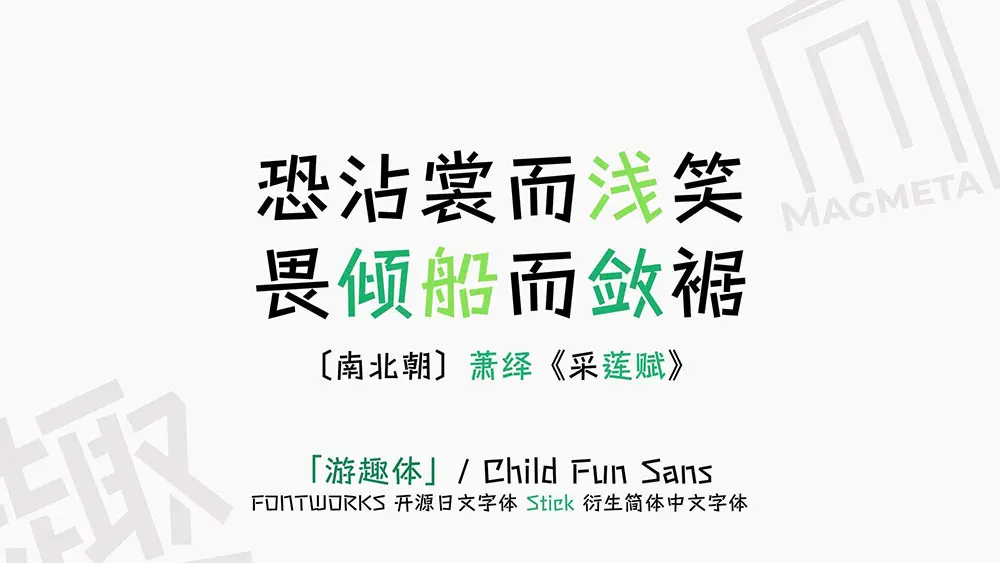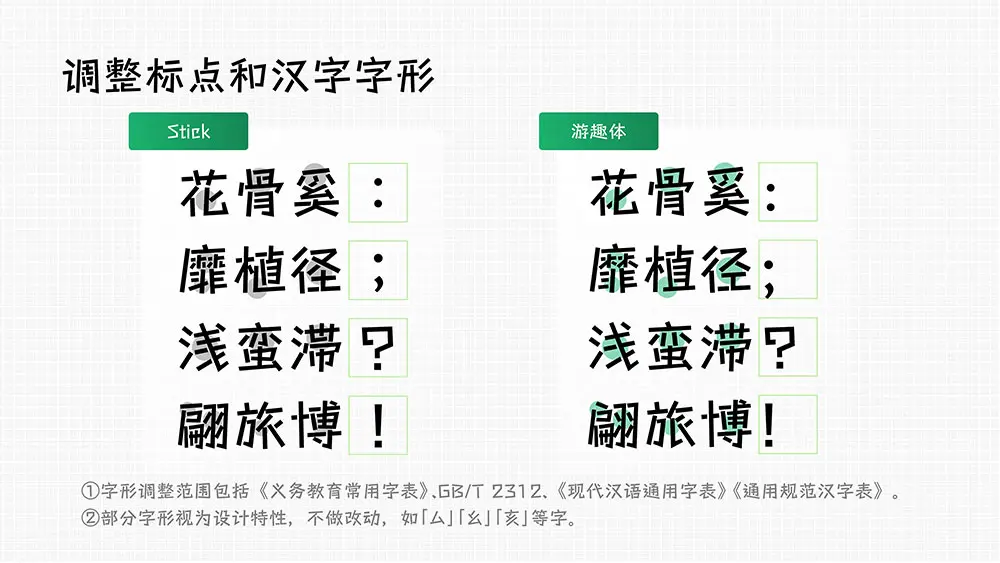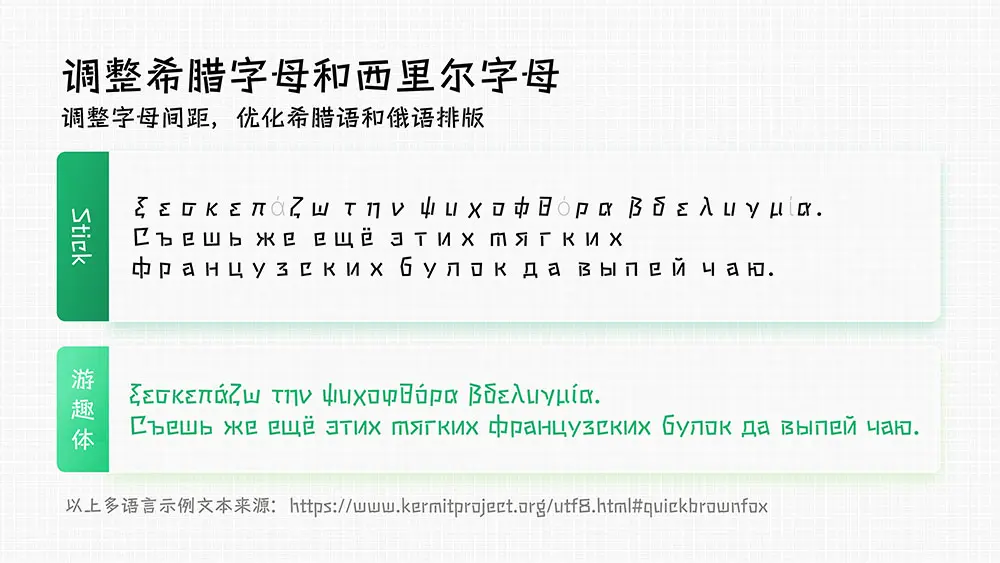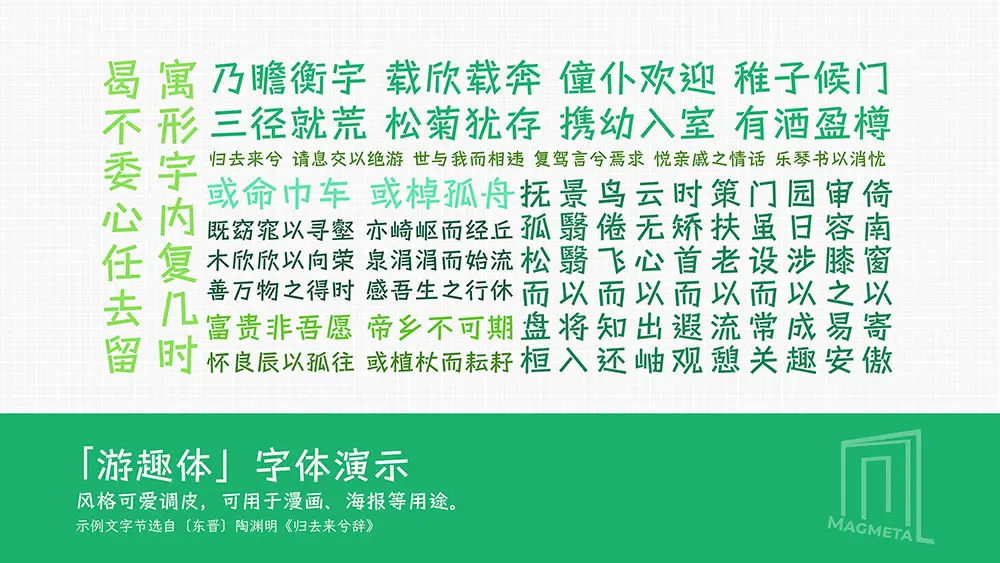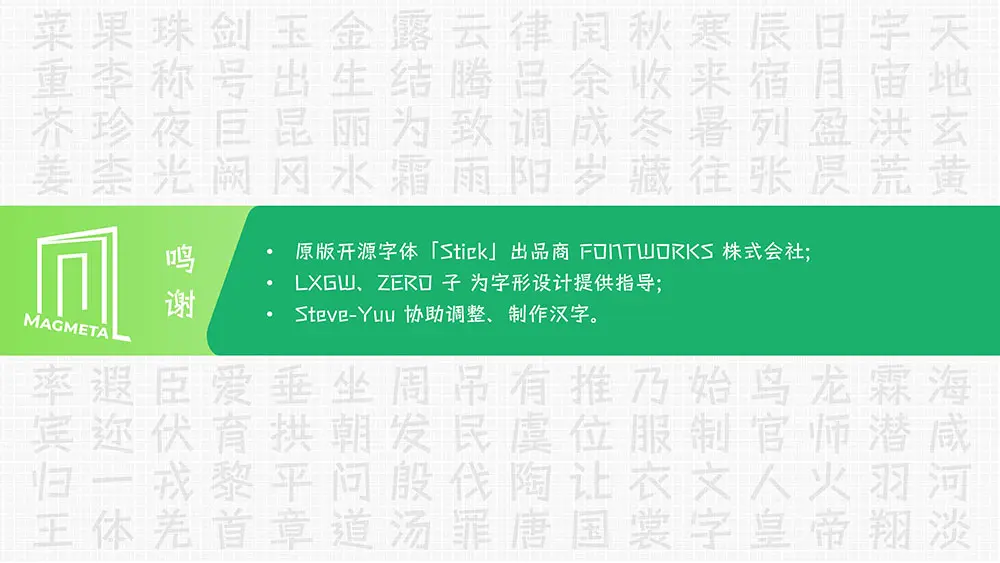
遊趣體介紹
遊趣體因筆形像筆桿一樣以直線設計,而被視為一款既可愛調皮,亦有田園寫意風格的字體,本人基於 Fontworks 出品的日文字體ステッキ / Stick 擴充、調整字形,並編輯、適當增加 OpenType 特性,以滿足簡體中文的使用需求。
繁體部分:由於該字體目前定位仍以簡體為主,目前無對原字體包含的繁體部分增補及修改的計劃
注意事項:本人並不是專業的設計師,並未考慮設計美感,所以看起來可能略醜,補進去的字與原版可能略有違和感,且在新補字符中部分字的輪廓曲線會有毛刺。此外由於時間倉促,並沒有多餘的時間細修,部分字的部件拼接會很生硬。在補齊 GB/T 2312-1980 前,此字體將出現一定的缺字可能。